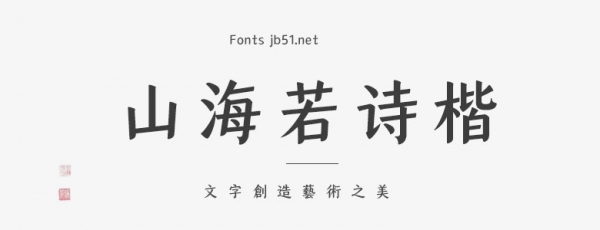
山海若詩楷是一款全新的楷體字體,是山海若詩楷字體家族系列中的特粗款,包含漢字9169個(gè),符號(hào)200+個(gè)。該字體字形優(yōu)美文雅,詩意內(nèi)斂,取楷體細(xì)膩的書寫筆畫,書法的運(yùn)筆走勢蘊(yùn)含其中,流暢自然,蘊(yùn)含東方審美韻味,盡顯優(yōu)雅從容,秀雅清新.